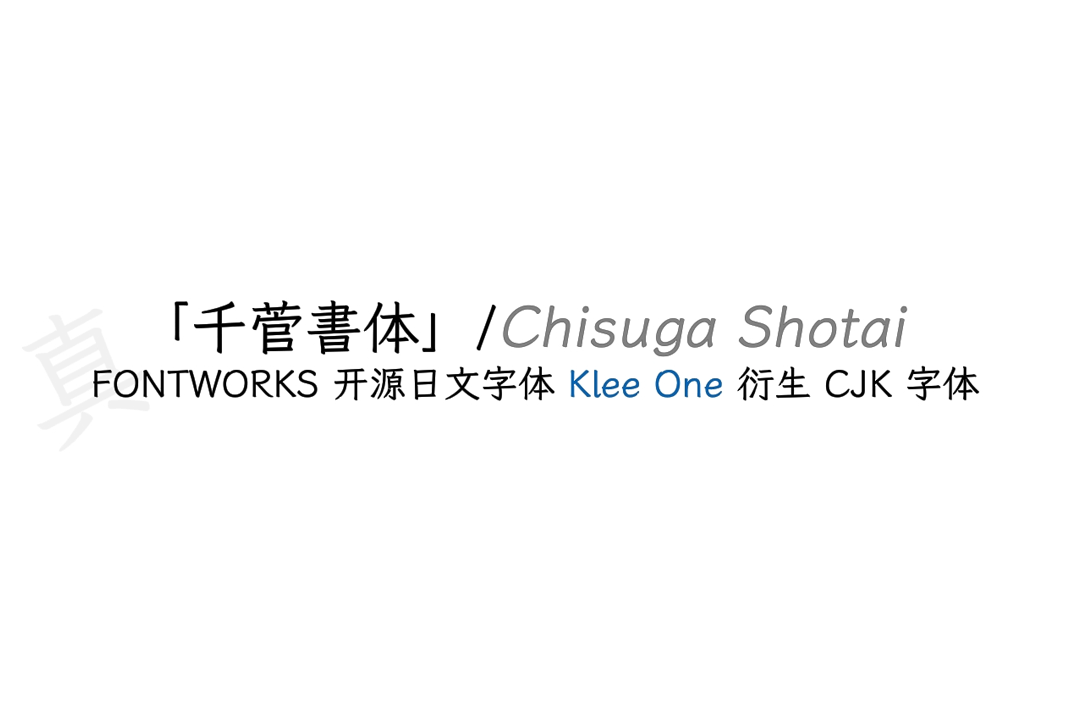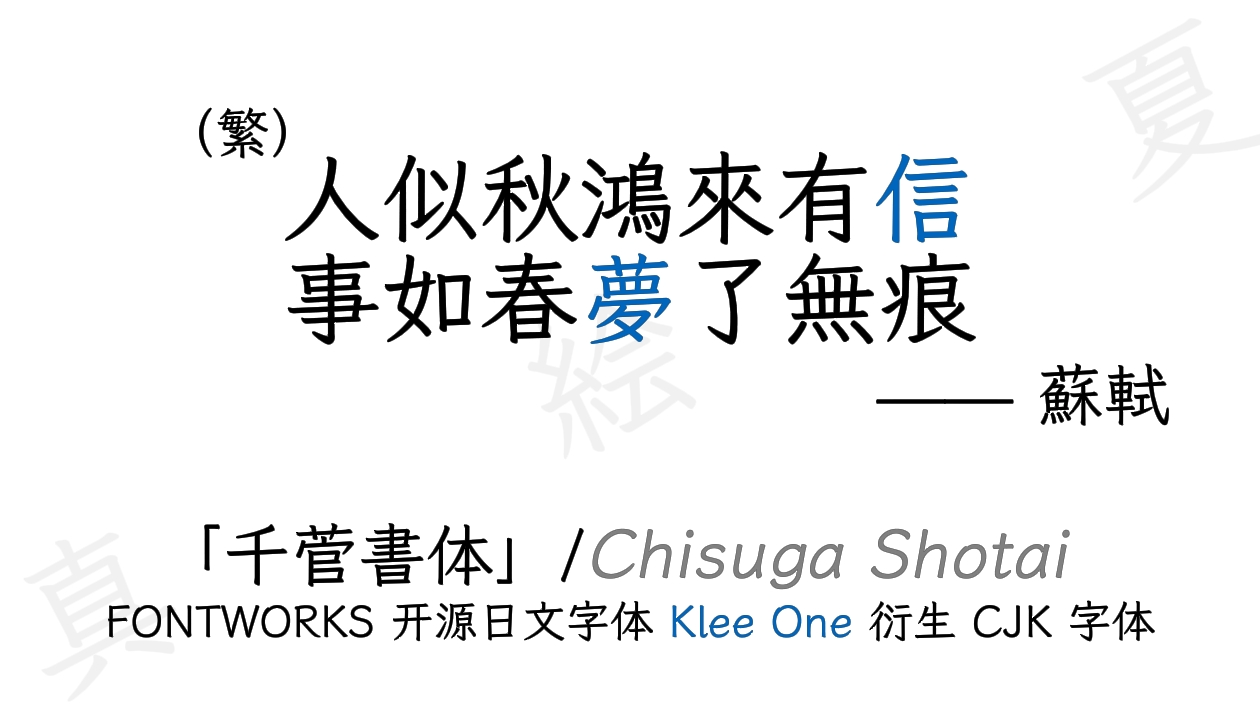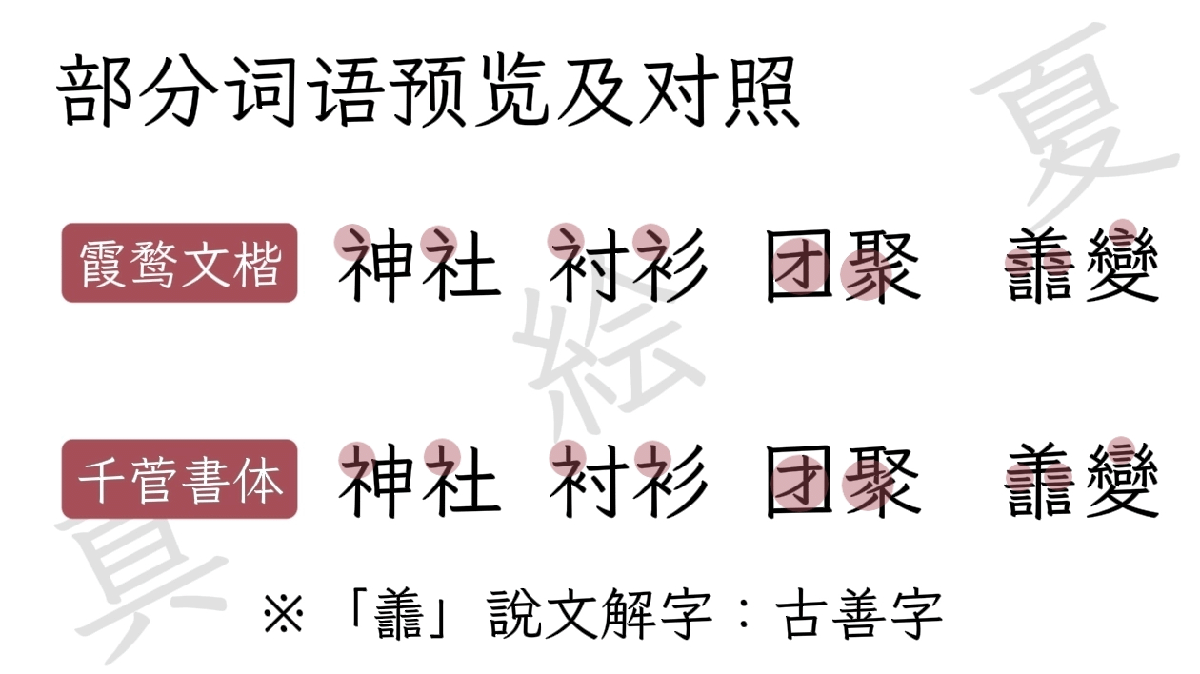
千菅書体(ChisugaShotai)_免费开源中文字体下载
千菅書体(ChisugaShotai)是一款适合中日文混排的开源中文字体,基于 Ysabeau、 Klee One、霞鹜文楷、末绮楷书、月星楷、Y式筆書衍生。
千菅書体(ChisugaShotai)偏近日本明朝体的字形风格且优先显示日本标准字形,但部分部件会有出入。